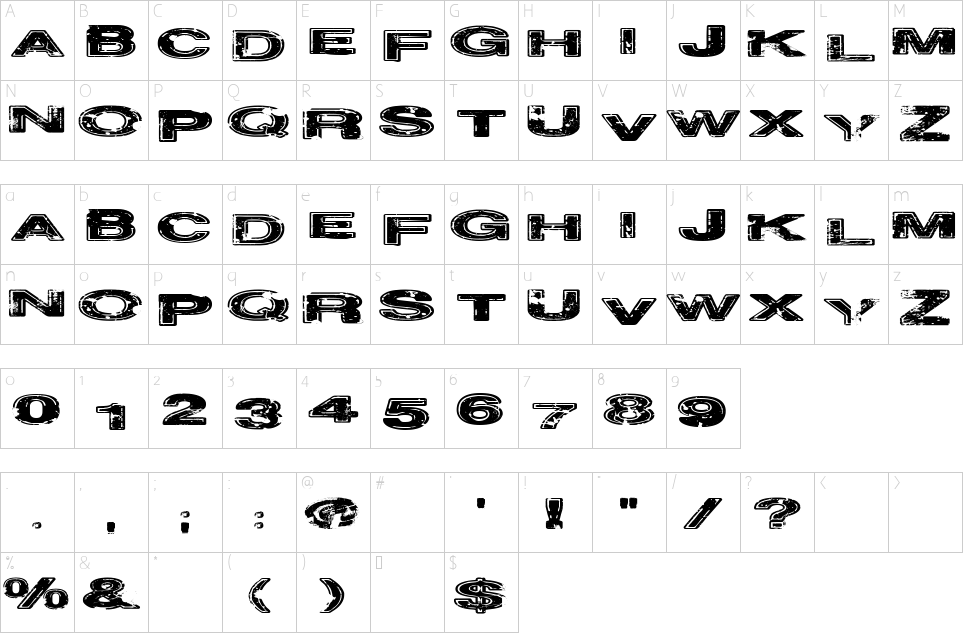
A fonte Project Z é uma opção grata para aqueles que estão em busca de uma fonte que ofereça uma abordagem natural e envolvente. Desenhada pelo designer Hanoded, esta fonte é ideal para projetos que buscam um equilíbrio entre elegância e facilidade. Com seu design cuidadosamente elaborado, Project Z é uma excelente escolha para criações digitais que exigem um toque de personalidade sem deixar de lado a estética mais clássica. Com a facilidade de download disponível tanto para Windows quanto para Mac, a Project Z torna-se uma fonte que você pode integrar em diversos ambientes de trabalho. Se você busca uma fonte que seja adequada para múltiplas aplicações, Project Z é uma ótima fonte para considerar.